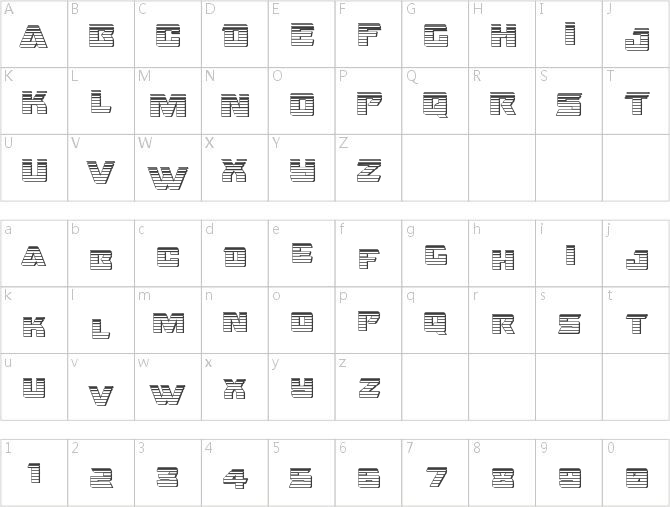
Oceanic Drift Chrome 詳情頁
字體名稱: Oceanic
Oceanic Drift Chrome
Oceanic Drift Chrome字體字庫是一款讓人賞心悅目、百看不厭的英文字體,適合各類廣告和產品包裝設計應用,字體大小0.09MB,格式為ttf字體,上傳用戶是凡客,作者/版權方為未知